说到黑板报设计,这可是从小学就要开始培训的一个技能。想要把黑板报设计好,可能就会涉及到美术,文学艺术等等一些综合知识比较强的东西,而黑板报一般是由报头,标语,插花,尾花等部分组成。想要把黑板报做得吸引人,好看一点,那么首先黑板报字体就非常关键,黑板报字体选择的比较好,就会让黑板报出众。那么黑板报字体怎么设计才能够更出众呢?想要让黑板报字体出众一点,首先要找对字体,字体设计有创意、好看的,自然就能够吸引大众的眼光。
黑板报字体想要设计的出众一点,也需要考虑到主体图案。黑板报的报头是为了体现整个版面的精神,而主体图案是为了能够突出报头的,要考虑的就是图不能够压字,字完全可以压在图上,这个时候黑板报字体就可以选择一些比较特别的字体,这样就能够让刊头字比较醒目一点。
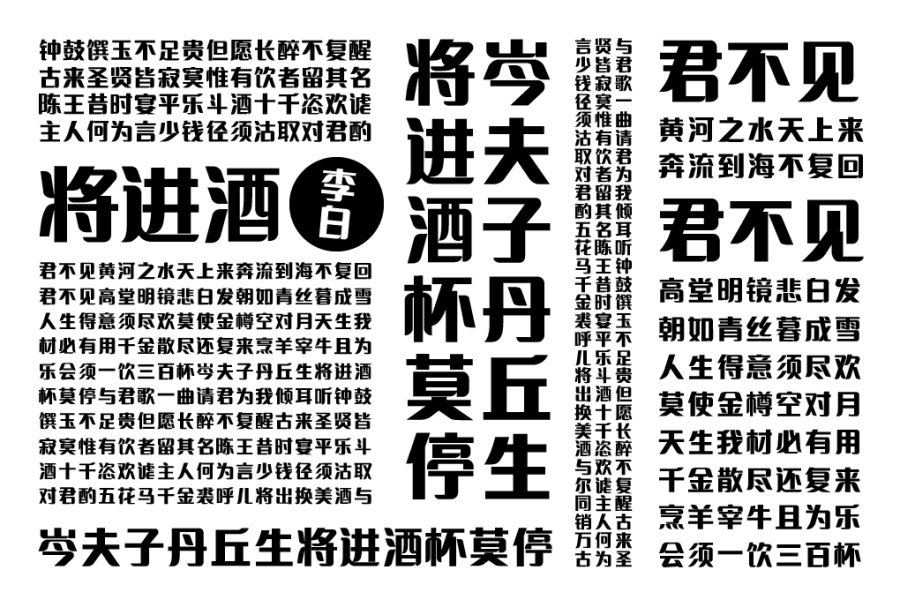
黑板报创意字体想要变得与众不同,那么除了考虑主体图案以外,还需要考虑排版问题。如果说黑板报字体的运用没有考虑到排版问题,那么整个版面,就会失去均衡感,没有稳定感,让人看着很不舒服,甚至还可能会拉低板报字体原有的美感。在选择黑板报字体的时候一定要考虑到版面的问题,毕竟版面的编排占有很大的成分,在设计运用的时候都需要考虑全面,这样设计出来的黑板报在直观上比较有美感。
黑板报字体在设计的时候肯定要考虑到画面的整体感,如果选择的字体没有考虑到这一点,那么,这就没有办法跟美术相融合,那么黑板报的整体效果,就会显得不够完美,版面也不够大方。所以在考虑黑板报字体的时候一定要考虑到画面的整体感是不是够均衡。